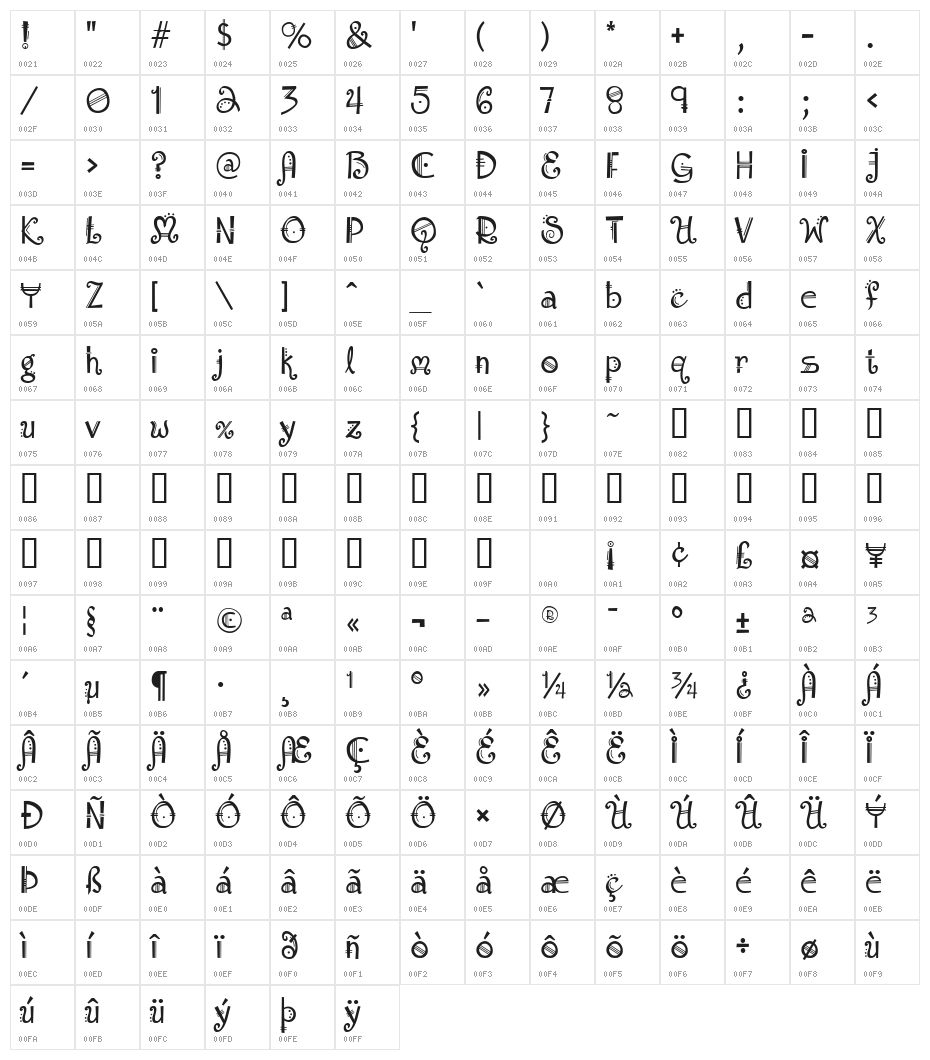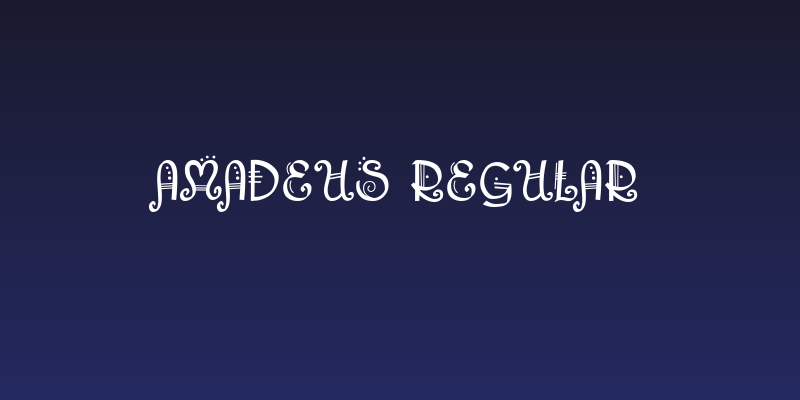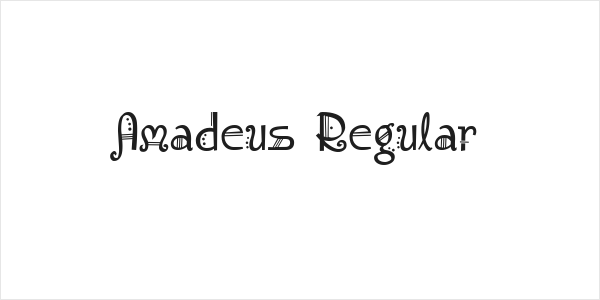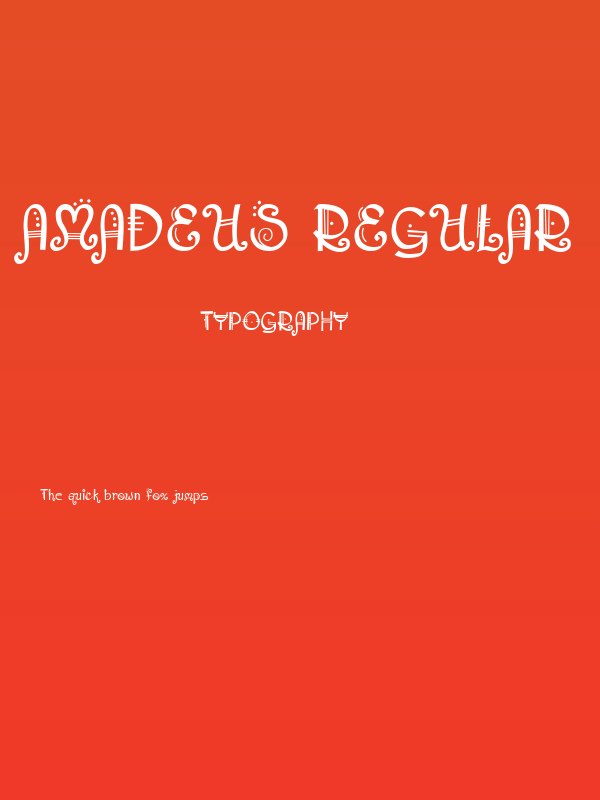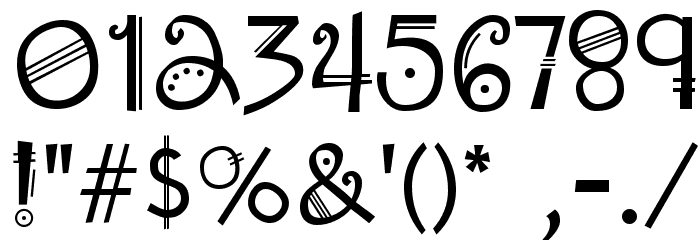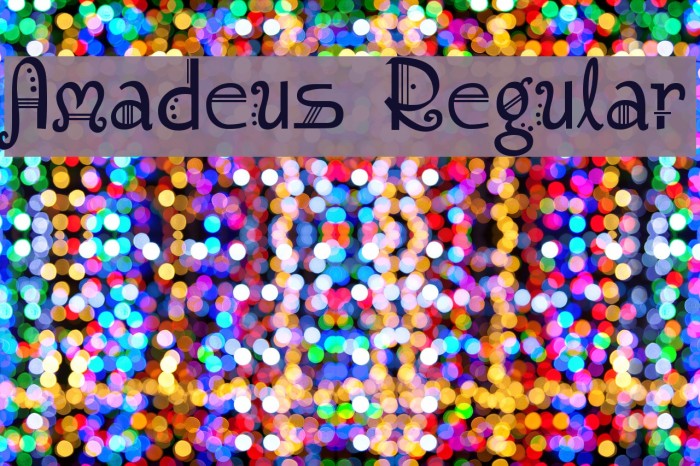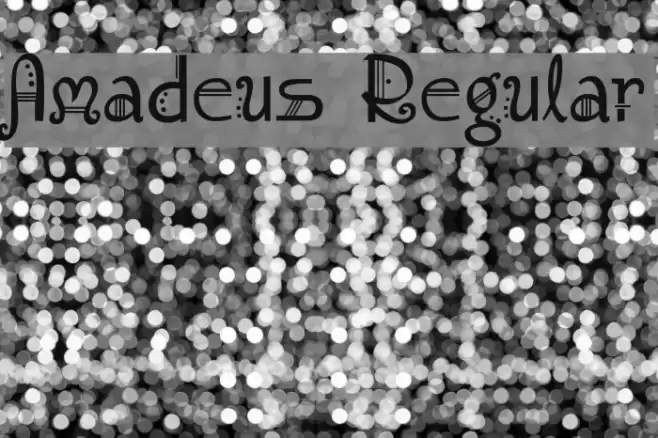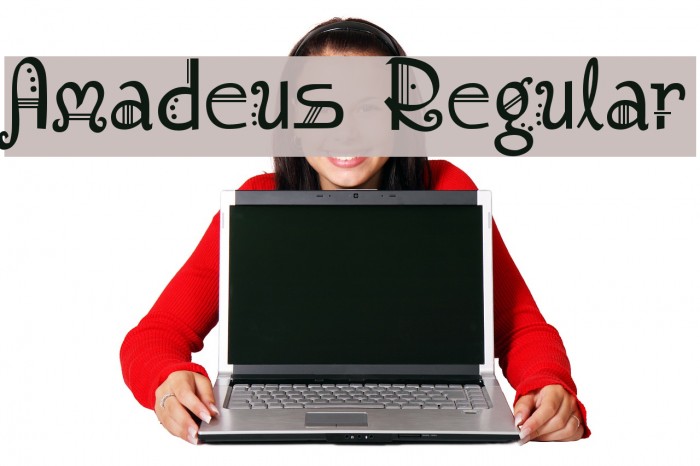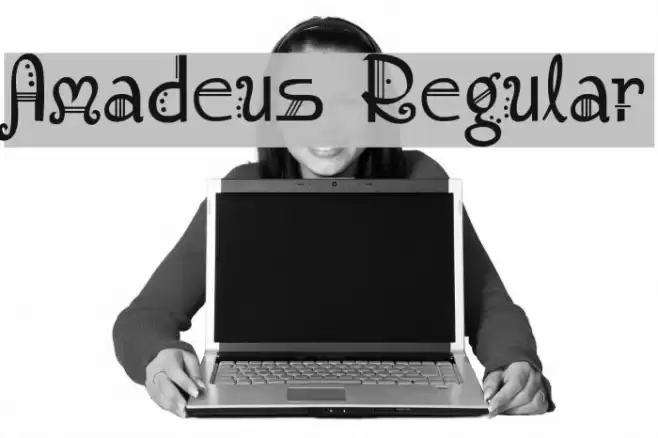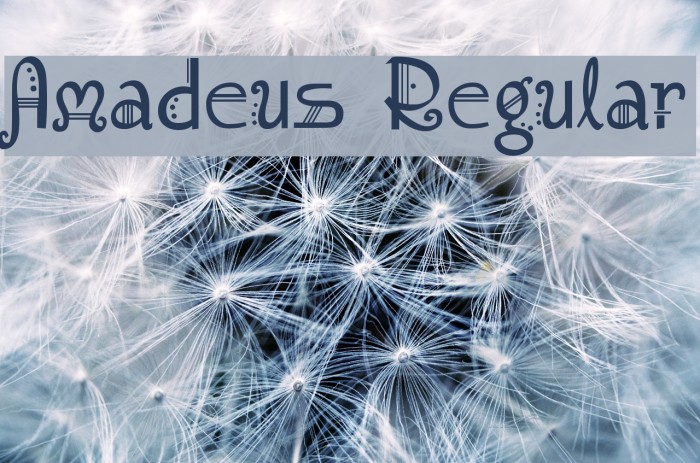
Amadeus Regular Font
| Proiecte propuse | Ideal for creative projects such as posters, invitations, album covers, and branding that require a unique and artistic touch. |